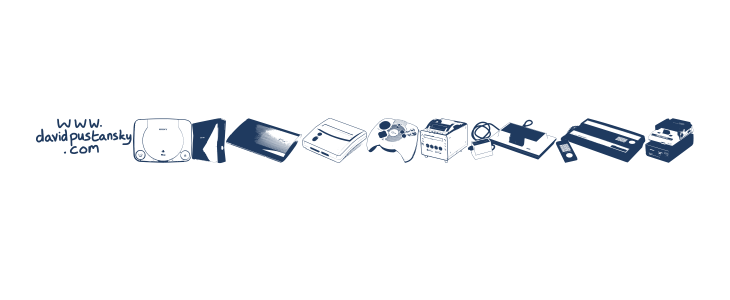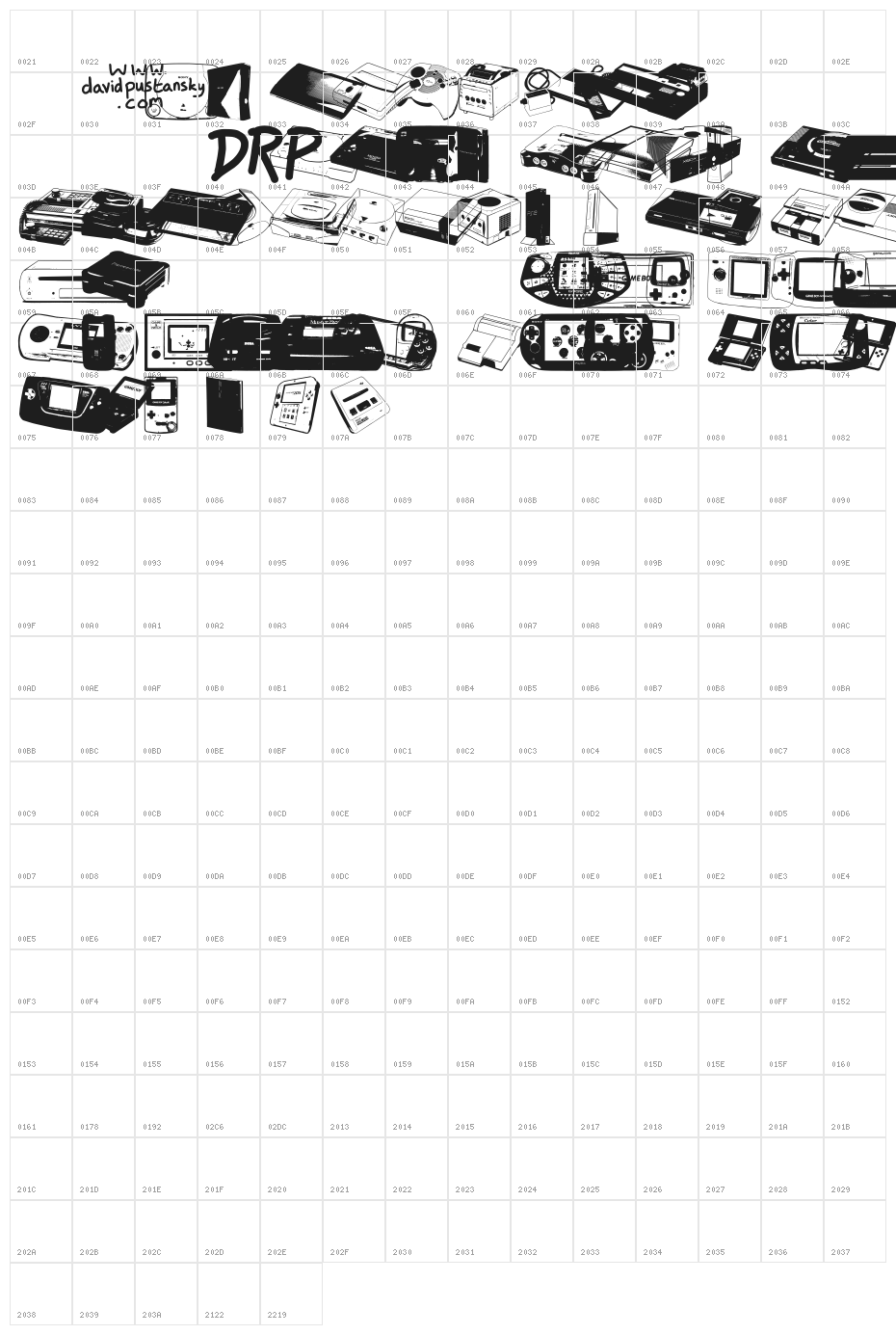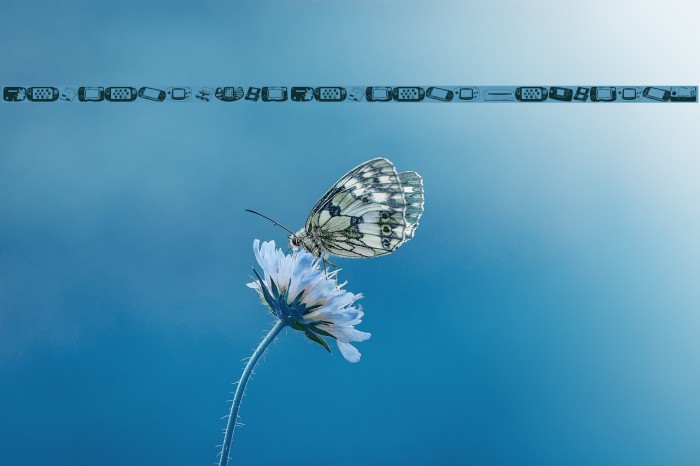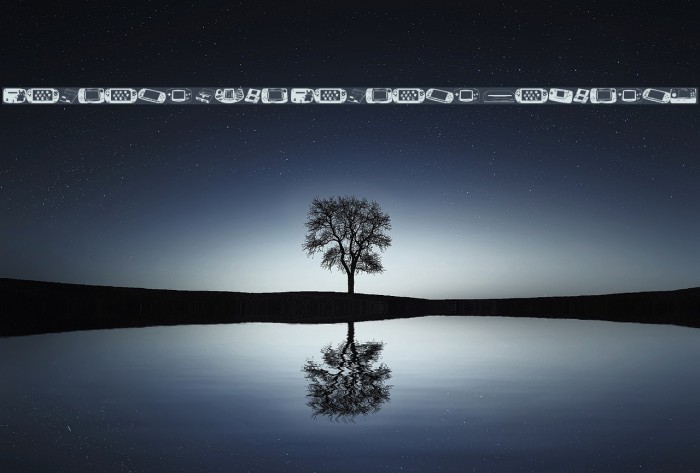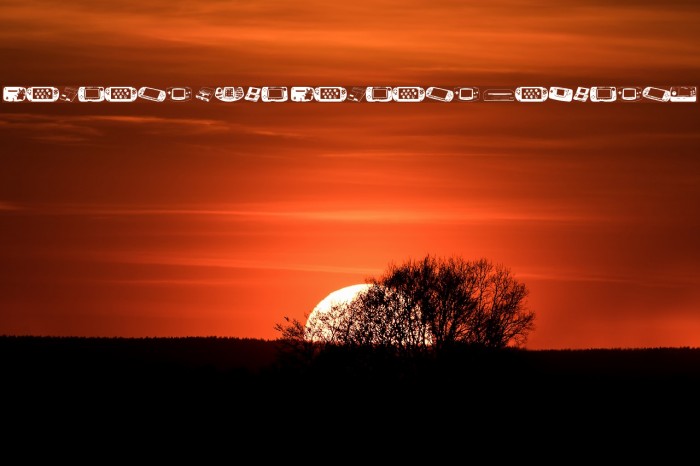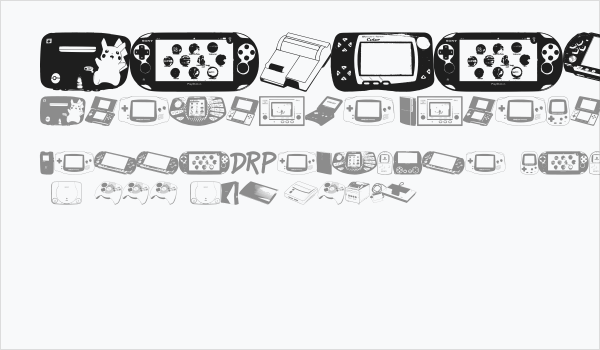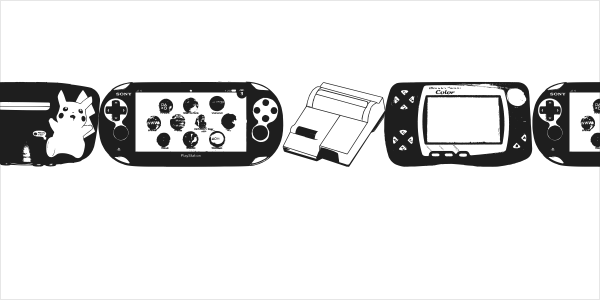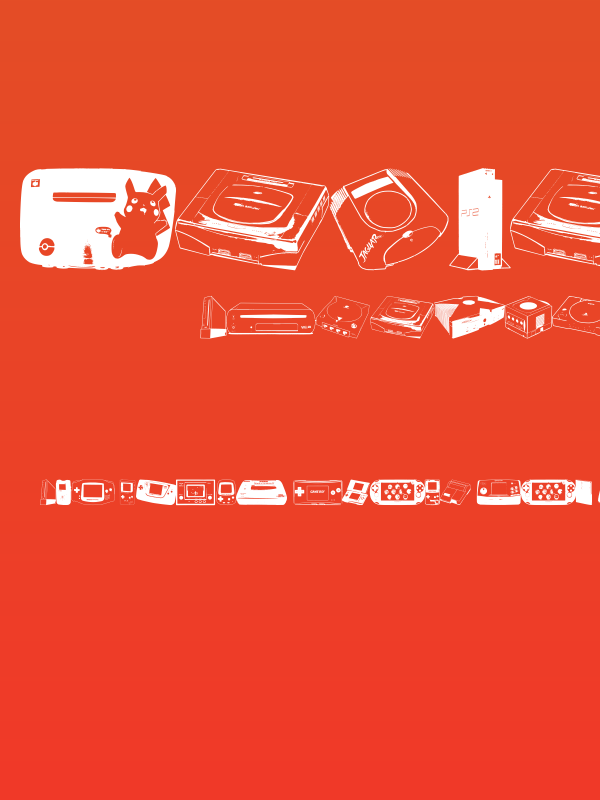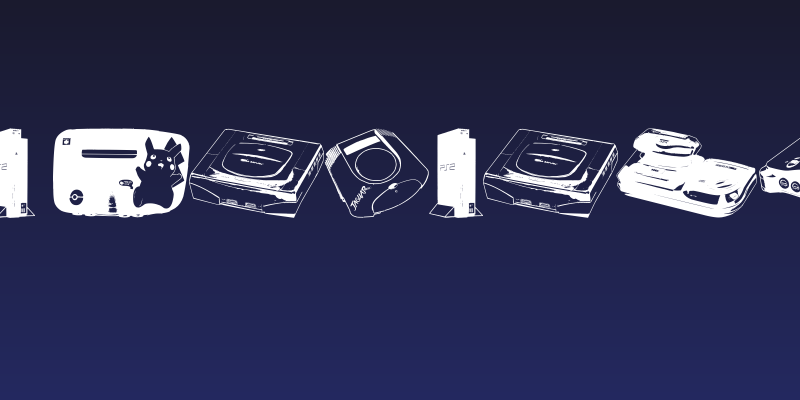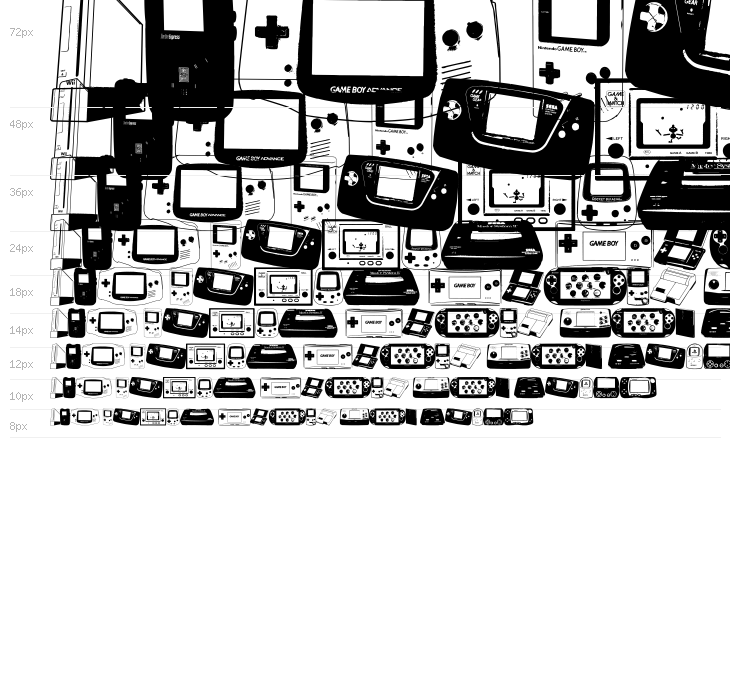
Console Wars Console Yourself Font
| Stile generale | Decorative, playful, retro-inspired |
| Caso d'uso | Logos, headlines, posters, themed graphics |
| Progetti proposti | Posters, t-shirt designs, gaming event branding, retro gaming websites, novelty merchandise. |